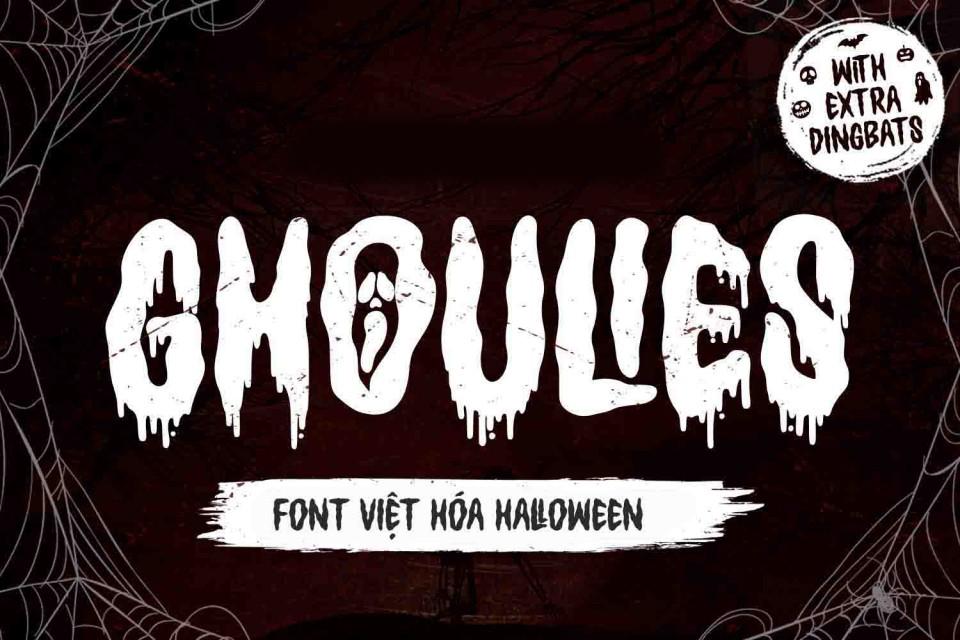
Font chữ Halloween Việt hóa là bộ sưu tập các phông chữ thuộc dòng Display mang phong cách kinh dị, ma mị, gai góc và tràn ngập không khí lễ hội hóa trang. Với các hiệu ứng độc đáo như nhỏ giọt máu, nét cào xước sắc nhọn hay hình thù quái dị, nhóm phông chữ này là lựa chọn hoàn hảo cho các thiết kế poster sự kiện, bao bì hộp quà tặng Halloween, nhãn dán kẹo (Trick-or-treat) và các ấn phẩm truyền thông độc lạ. Doozypack.vn cung cấp link tải trọn bộ phông chữ chuẩn kỹ thuật, giúp bạn sở hữu kho Font chữ Halloween Việt hóa Free chất lượng cao, hỗ trợ đầy đủ tiếng Việt để tự tin thiết kế bao bì và bộ nhận diện thương hiệu sự kiện.
Đặc điểm thẩm mỹ độc đáo của bộ font chữ Halloween
Phông chữ Halloween không đi theo sự chuẩn mực hay thanh lịch; nó mang đến một ngôn ngữ thị giác đầy tính kịch tính, tái hiện trọn vẹn sự huyền bí và rùng rợn của đêm hội hóa trang.
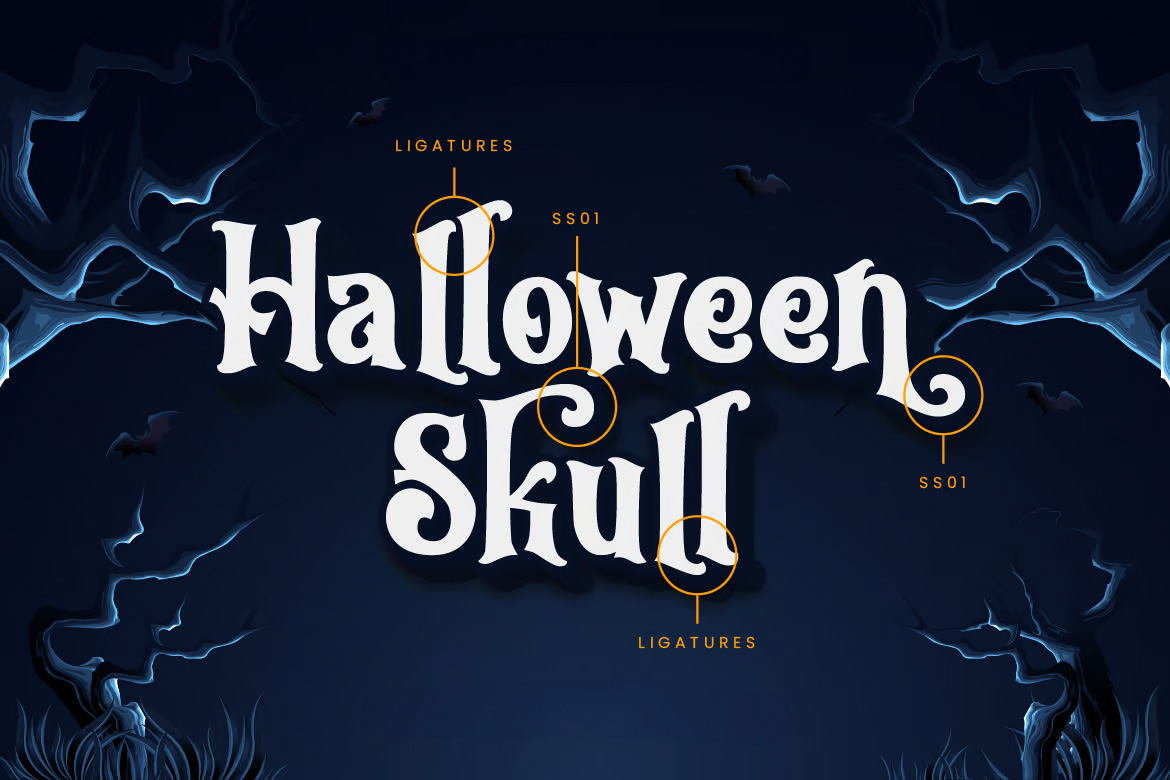
Phong cách Spooky ma mị và hiệu ứng nhỏ giọt (Drip Effect)
Đặc trưng lớn nhất của các bộ Font chữ Halloween Free là các chi tiết tạo hình vô cùng sáng tạo: từ những giọt máu nhỏ giọt từ đỉnh chữ, những nhánh cây khô gai góc bao quanh ký tự cho đến hình thù xương xẩu, ma quái. Thiết kế này tạo ra một sức nặng thị giác vượt trội, giúp tiêu đề trên bao bì hoặc poster ngay lập tức thu hút ánh nhìn, kích thích sự tò mò và mang lại cảm giác phấn khích cho người xem.
Cấu trúc chữ gai góc tạo không khí lễ hội rùng rợn
Các ký tự sở hữu độ dày nét biến thiên linh hoạt, kết hợp cùng các góc nhọn sắc lẹm hoặc các nét đứt gãy táo bạo. Sự bất quy tắc này tạo nên một nhịp điệu Typography vô cùng ma quái, giúp các câu slogan hay tên chương trình sự kiện toát lên vẻ huyền bí, rất phù hợp với các sản phẩm giới hạn (Limited Edition) trong mùa lễ hội tháng 10.
Ưu điểm nổi bật của bản Font chữ Halloween Việt hóa Free
Khi ứng dụng các phông chữ trang trí chủ đề kinh dị vào thị trường trong nước, sự chỉn chu về dấu câu là yếu tố quyết định đến tính chuyên nghiệp của ấn phẩm:
- Khắc phục triệt để lỗi dấu tiếng Việt: Phiên bản Việt hóa đã được đội ngũ thiết kế trau chuốt thủ công từng dấu câu. Các dấu sắc, huyền, hỏi, ngã, nặng được vẽ với phong cách quái dị đồng điệu cùng thân chữ gốc, không gây cảm giác chắp vá hay làm đè nét làm mất tính thẩm mỹ.
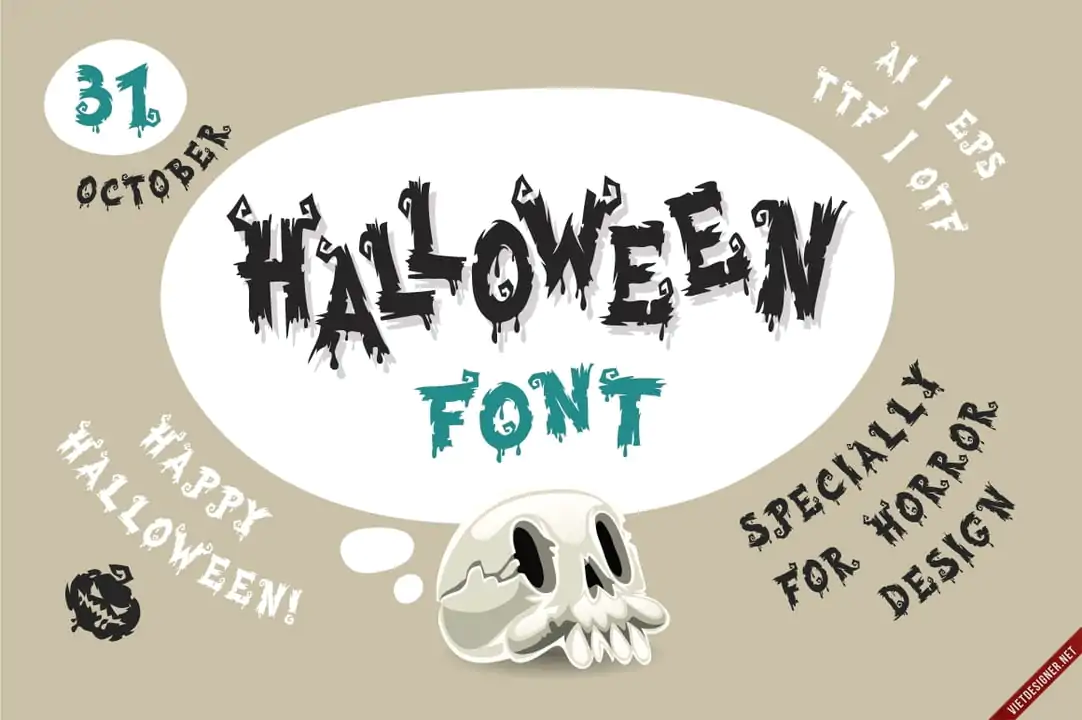
| Nhóm Font Halloween | Đặc điểm thị giác | Ứng dụng đề xuất tại Doozypack.vn |
| Font Nhỏ Giọt (Dripping) | Hiệu ứng máu chảy, quái dị, ấn tượng | Làm tiêu đề chính hộp bánh kẹo Trick-or-treat, poster sự kiện. |
| Font Xương Séc (Skeletal) | Góc cạnh, gai góc, rùng rợn | Thiết kế nhãn dán đồ uống, hộp quà tặng Halloween độc lạ. |
| Font Retro Horror | Cổ điển, ma mị, phim kinh điển | Dùng cho thiệp mời tiệc hóa trang, túi giấy sự kiện. |
- Tem nhãn dán Sticker trang trí: Cấu trúc chữ quái dị rất thích hợp để in các tem decal dán lên ly nước, hộp quà hoặc làm sticker trang trí phòng tiệc, mang lại sự hào hứng cho người tham gia.
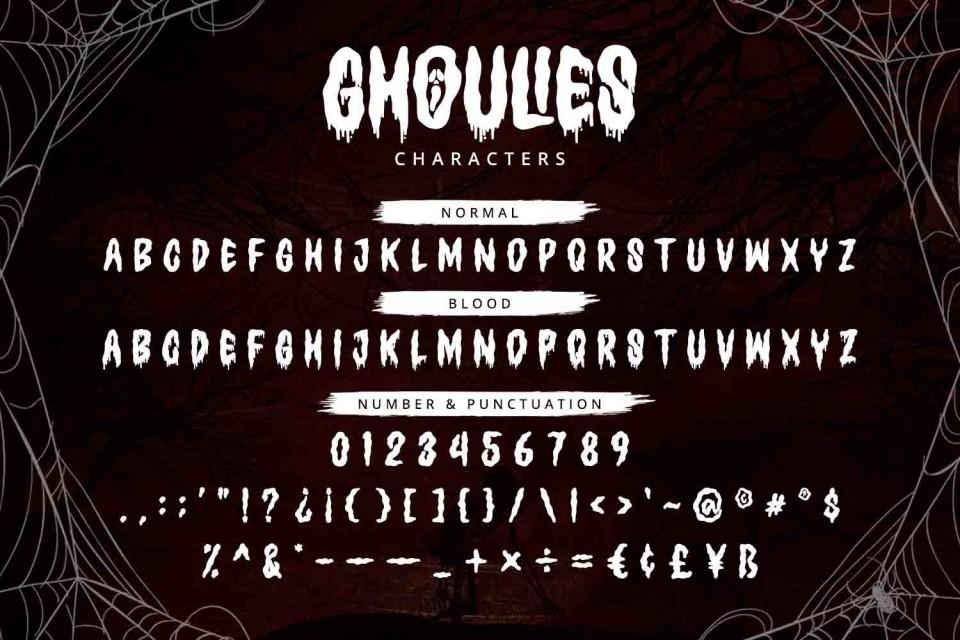
Lưu ý kỹ thuật khi in ấn với phông chữ kinh dị ma mị
Việc sản xuất bao bì thực tế sử dụng các phông chữ có đường nét phức tạp đòi hỏi sự am hiểu kỹ thuật chuyên sâu tại xưởng in Doozypack.vn:
- Kiểm soát hiện tượng tràn mực (Dot Gain) tại chi tiết nhỏ: Các hiệu ứng nhỏ giọt hoặc nét đứt của font Halloween có diện tích khá nhỏ. Khi in trên giấy có độ thấm mực cao như giấy Kraft, mực có thể bị lan làm bít kín các chi tiết này. Bạn nên giữ size chữ tiêu đề tối thiểu từ 10pt trở lên.